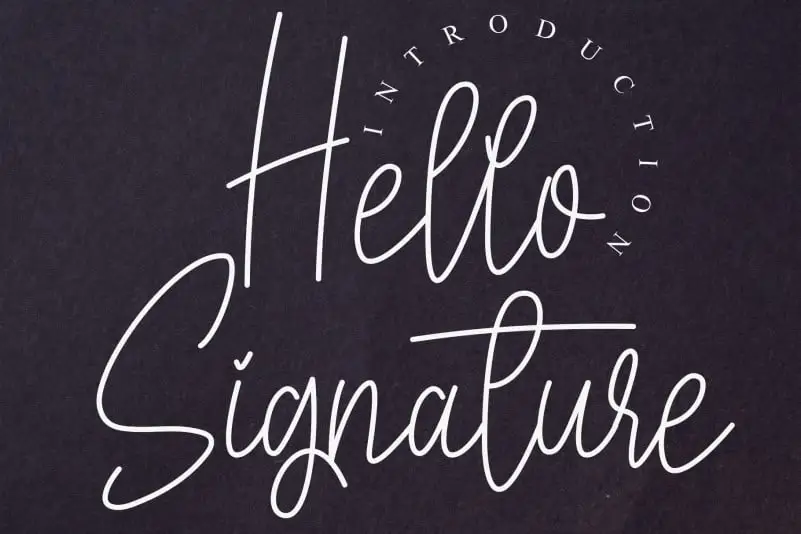
Hello Signature Script Font – Download Grátis
A fonte “Hello Signature Script Font” oferecida pela designer creativeletter traz uma experiência única e especial aos usuários. Com seu traço elegante e detalhado, essa fonte é ideal para criar mensagens pessoais e autênticas, perfeita para assinaturas exclusivas ou gráficos de alta qualidade. Seu design curvilíneo permite que você personalize suas criações com flexibilidade, desde pequenos elementos até grandes projetos. Ideal tanto para aqueles que buscam uma fonte diferenciada como para designers que desejam adicionar um toque único ao seu trabalho. Esta fonte é perfeita para quem busca expressar a individualidade em cada projeto. Seja você criando mensagens personalizadas ou desenvolvendo gráficos de alto nível, o Hello Signature Script Font oferece uma maneira única e sofisticada de fazer isso. Não importa se está trabalhando no design de site, criação de material publicitário ou mesmo em ilustrações digitais, essa fonte traz a essência da autenticidade e personalização que você precisa para destacar seu trabalho nas mãos do público.